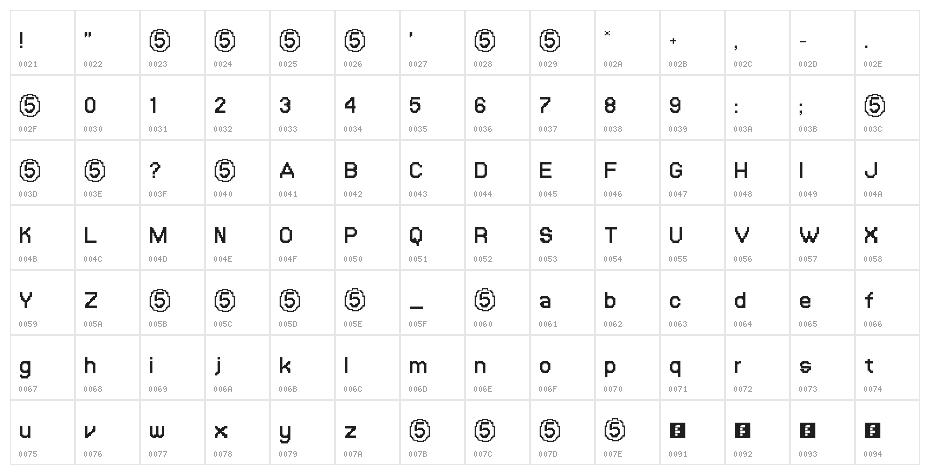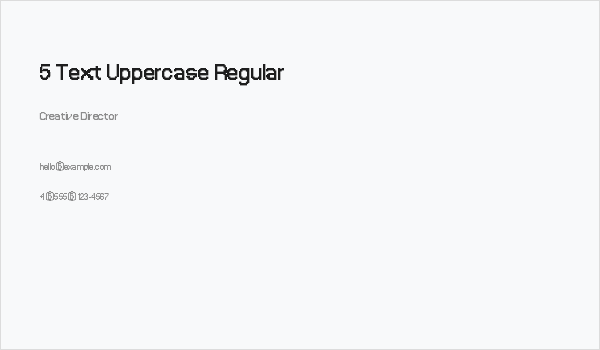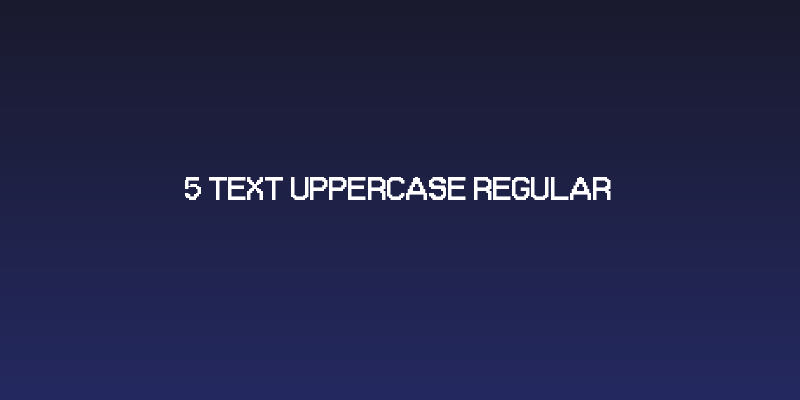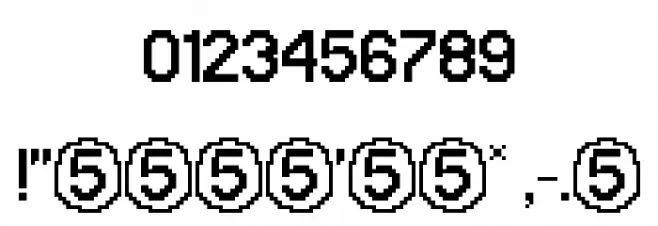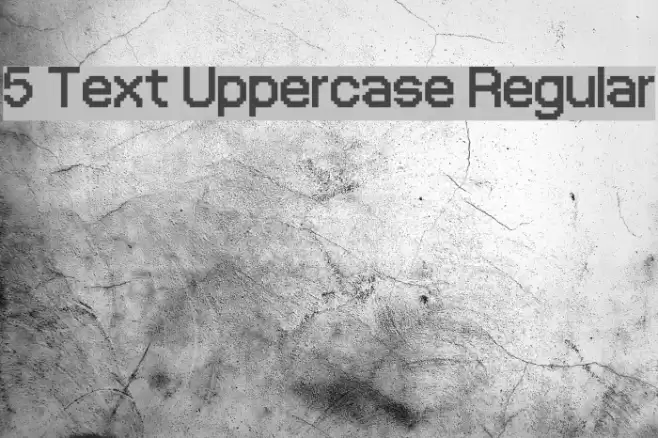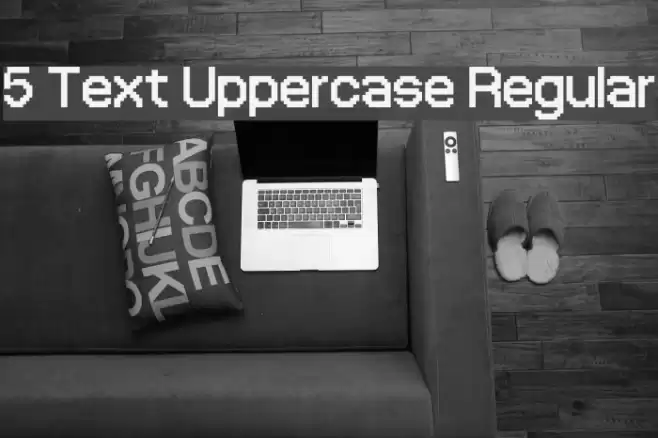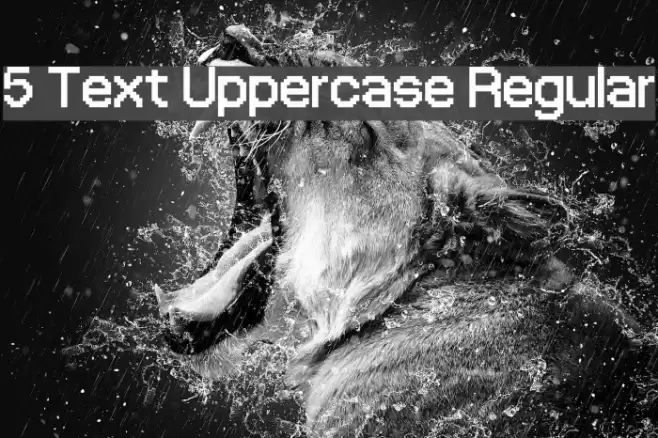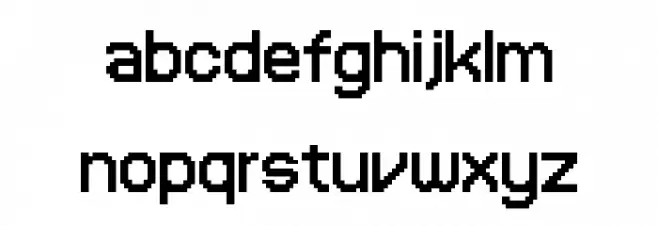
5 Text Uppercase Regular Font
✎ Pixel
| श्रेणियाँ | Pixel |
| समग्र शैली | Vintage |
| उपयोग का मामला | Logos, Digital displays, Retro-themed projects |
| सुझाए गए प्रोजेक्ट | Ideal for retro video games, digital art projects, tech-themed designs, and nostalgic branding. |